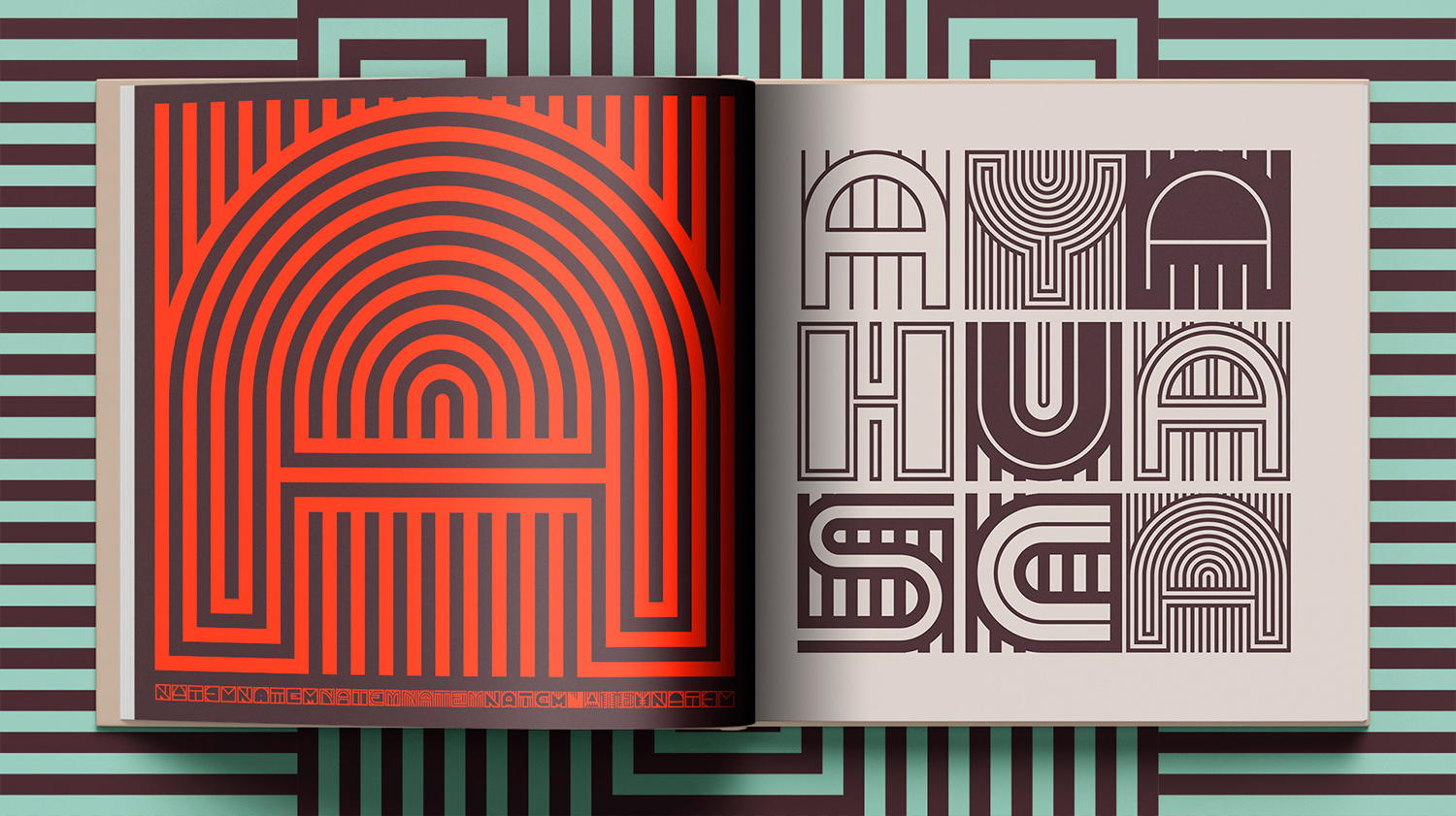
Llegamos a la sexta entrega de la serie que dedicamos en Rayitas Azules a las mujeres latinoamericanas en tipografía y, en esta ocasión, nos desplazamos a Ecuador para conocer la originalísima obra de Vanessa Zúñiga.
Ante todo, una humanista
Vanessa Zúñiga se escapa a cualquier intento de definición. No se trata solamente de que la tipografía experimental juegue un papel esencial en su obra o de la creación de patrones y piezas modulares a partir de piezas arqueológicas de culturas ancestrales latinoamericanas; es, sobre todo, la riqueza, ambición y profundidad del planteamiento conceptual de su trabajo. En su universo gráfico se entremezclan tipografía, diseño gráfico, arqueología, antropología e historia. Por ello, podríamos decir que ella es, por encima de todo, una humanista. «Crónicas Visuales del Abya Yala es el nombre que le coloqué hace 14 años a la parte de exploración visual del proyecto de investigación. Es un proyecto personal en el que estoy trabajando desde hace 17 años y que se enfoca en registrar los experimentos que realizo con signos visuales de las culturas originarias de Latinoamérica que he ido recopilando y simplificando a partir del análisis de piezas arqueológicas, textiles, pinturas faciales, entre otros. A lo largo de estos años he demostrado que estos signos pueden ser reinterpretados y reutilizados para crear nuevos símbolos, y compartir, a través de ellos, nuestra historia, mitos y saberes ancestrales, bajo un proceso de recontextualización que permita revalorizar, celebrar, amplificar y traducir globalmente la memoria histórica de Latinoamérica.»
Crónicas Visuales del Abya Yala
Azares
Vanessa Alexandra Zúñiga Tinizaray nació en Loja, una pequeña ciudad al sur de Ecuador. Por uno de esos inesperados avatares de la vida, acabó estudiando Diseño y se enamoró irremediablemente de la disciplina, lo que la llevó, una vez acabada la carrera en su país, a ampliar estudios en la Maestría de Diseño de la Universidad de Palermo, en Buenos Aires, Argentina. «Llegué a la Universidad de Palermo con un retraso de tres semanas por temas de trámites de mi visa de estudiante y cuando llegué todos mis compañeros ya estaban enfocados en sus temas de tesis y yo no tenía ninguno. En esos días tenía que ir a una tienda de antigüedades ubicada en el barrio Recoleta, en Buenos Aires, para agradecer a unos familiares de mi cuñado por ayudarme con un papeleo para ingresar en la Universidad. Cuando estaba frente a ellos, me preguntaron qué tal me iba en mis primeros días en Buenos Aires. Les comenté que estaba un poco perdida con la selección del tema de tesis, que si bien me gustaba leer sobre historia, quería enfocar cosas relacionadas con la mitología griega y el diseño .Tengo tan presente en mi mente su expresión, ya que eran dos personas las que estaban frente a mí, que se miraron entre sí. Uno de ellos se acercó a su estante de libros y sacó un vetusto libro de Ricardo Rojas que se llama “Silabario de Decoración Americana” y me dijo, “toma, míralo”. Abrí el libro y nuevamente no hubo vuelta atrás. Recorrí esa primera vez con mis ojos cada hoja del libro y entendí, sin que me lo hubieran dicho, lo que esa mirada entre ellos significó. “Tenés tanto potencial en la historia de tu país, solo que no te has dado cuenta, y quieres mirar hacia otras culturas que no tienen nada que ver con la tuya.” Esto es lo que yo me imagino estaban pensando, con acento argentino, claro.»
Pero no todo queda ahí. Lo más interesante de los azares de la vida es tener la capacidad para identificar que ese camino que se abre inesperadamente podría ser el de una. «Luego de unos dos meses me ayudaron a conseguir el libro a través de un museo, ya que es una edición vieja y no era tan fácil de obtener. Mientras tanto, el azar hizo que el lugar donde yo estaba viviendo en Buenos Aires, en la calle Charcas, quedara a cuadra y media de la casa-museo de Ricardo Rojas y algunas tardes de invierno fui a refugiarme ahí para poder leer el libro hasta que lo lograse conseguir. Ese fue el inicio de todo.»
Proceso creativo
El planteamiento de Zúñiga es minucioso, muy atento al detalle y con una relación muy cercana a la artesanía, a lo manual —en un sentido conceptual, más allá de las herramientas empleadas—, y con una cierta base en el método científico. «A cada registro que realizo le coloco un número y un nombre. Selecciono una pieza arqueológica por distintas razones, un textil, construcción arquitectónica, pintura facial u otro elemento. Analizo si hay investigaciones del objeto que voy a estudiar, o referencias que me guíen a realizar un ensayo de interpretación, pero normalmente tomo piezas que los museos ya tienen estudiadas. Los museos han mejorado notablemente sus plataformas en línea, eso me ayuda enormemente. La primera fuente que hice fue una mezcla de dos piezas arqueológicas, me demoré como tres meses en hacer las 26 letras, me aburría y volvía. Cuando tuve el resultado la miré y me dije «de acá salen dos fuentes», dejé la una de lado y pulí la segunda. Hasta eso ya estaba en mi registro número 15 y esa fuente se llamó Sara, a la que le tengo un cariño personal porque fue el inicio de mi amor por la tipografía y con la que inicio mi presentación en la charla que tengo destinada para hablar sobre las culturas de los andes y a través de ella cuento un poco sobre la cosmovisión andina.»
Torrente de creatividad
Vanessa es torrencial. El valor de su trabajo está fuera de toda duda, pero su secreto reside en su postura hacia la labor creativa, heterodoxa, desprejuiciada, lejos de imposturas y sin el menor temor a transitar senderos insospechados. Inventar un camino propio y andarlo. Esta es una gran lección.
Además, posee una poderosa voz propia. Merece la pena escuchar lo que nos tiene que contar.
Bifurcaciones
O vasos comunicantes. El trabajo de Vanessa se reparte en diferentes encarnaciones, según su propia naturaleza.
- «Amuki es un estudio de diseño y laboratorio experimental, un espacio de interacción productiva de saberes, técnicas y disciplinas distintas, pero convergentes, con el objetivo de generar cambios cualitativos en el diseño y en su enseñanza; un espacio para imaginar y diseñar nuevos escenarios, objetuales, visuales y comunicacionales, apto para el despliegue fluido del pensamiento creativo y, a la vez, sensible a las demandas de la sociedad.»
- «Tras los años de estudio en Buenos Aires, retorné a mi ciudad en el 2007. Durante los primeros cinco años tras mi vuelta, tomé algunos proyectos comerciales y en mi tiempo libre iba realizando los experimentos del proyecto de investigación. Entre crisis personales y superar mis altibajos emocionales, en el año 2012 las cosas cambiaron y el proyecto fue tomando forma y empezó a requerir más tiempo. Poco a poco, dejé de tomar proyectos comerciales para enfocarme en explorar otras áreas, como empezar a aplicar los resultados de las exploraciones en productos, así nació a finales del 2014 mi marca Rukuyaya.» En ese contexto creativo fue donde nació «mi carta de presentación profesional al mundo, el libro Crónicas Visuales del Abya Yala, que en 2014 obtuvo dos menciones en la Bienal Iberomaericana de Diseño, y en el 2017, un Certificado a la Excelencia Tipográfica del Type Directors Club de NY.»
- «Actualmente, además de estar enfocada en el proyecto de investigación, doy talleres sobre modularidad a través de Zoom a grupos pequeños y en universidades en los fines de semana para poder enfocarme los días de la semana en la investigación. En esta misma línea, doy charlas en eventos de diseño y universidades donde hablo sobre los distintos registros del proyecto de investigación, y a través de ellos he podido conocer a grandiosos colegas que se han convertido en mis amigos.»
Vertiente comercial
«Tengo una tienda online de mi marca Rukuyaya, que nació con la intención de mostrar en mis conferencias los resultados de la investigación, pero en productos reales. Por ahora, por el tema de la pandemia, decidí parar cualquier tipo de producción, pero espero en el futuro poder retomarla. Trabajo con artesanos de mi ciudad y es una experiencia diferente que me hace dejar de estar todo el día frente al computador. En el proceso de desarrollar productos para la tienda, aprendí a bordar con mullos y cuando deseo descansar de lo digital me dedico a mis proyectos tipográficos análogos.»
Tipografía modular
«Una vez que conecté modularidad (a partir de piezas arqueológica motivo de estudio) y tipografía, me adentré en el mundo de la tipografía modular y empecé a estudiar distintas metodologías que me permitiesen trabajar de forma más eficiente. Y, como todo lo que ha llegado a mi vida, no hubo vuelta atrás. Lo he ido perfeccionando a través de estos años, y ahora enseño estas metodologías en mis talleres. En el año 2012 tuve mi primer acercamiento al processing. Me lo mencionó un amigo y me compré un libro llamado Generative Design. A partir de ahí, me empecé a dar cuenta de que había otra forma de trabajar con el tema de módulos que no era hacerlo manualmente uniéndolos uno por uno. Luego me adentré a buscar más metodologías que me pudiesen ahorrar tiempo y las fui sumando a mis experimentos. Así conocí Processing y NodeBox 3, editores de fuentes que me permiten realizar patterns fonts, y cada vez que aprendo algo trato de perfeccionarlo y ajustarlo a mis necesidades para luego enseñar estas metodologías en los talleres.»
La mejor educación
«Me encanta dar talleres a las personas que quieren aprender las distintas metodologías que aplico, y más que nada porque son de distintas edades. Tengo el ejemplo de mi padre de que no hay edad para seguir aprendiendo y alimentando el cerebro. Él tiene 72 años y lo veo experimentar con sus circuitos integrados, haciendo carpintería o aprendiendo a programar. Cuando voy a visitarlos y me quedo unos días con ellos, al llegar la noche lo veo instalarse en la sala de estar y colocar sus videotutoriales para, al siguiente día, ponerse a hacerlos. La mejor educación es el buen ejemplo. Así que dentro de lo rara que puedo parecer, sí me gusta estudiar, aprender, experimentar y proponer. Creo que de las cosas que más quedaron en mi mente de las enseñanzas de Gustavo Valdés, mi tutor, fue que «si quieres demostrar todo lo que estás dejando escrito en estos papeles, tendrás que hacerlo”. Y así lo he estado haciendo estos años, porque, como dice mi papá, «el papel aguanta todo, pero si no se enseña con hechos, todo queda en palabras».»